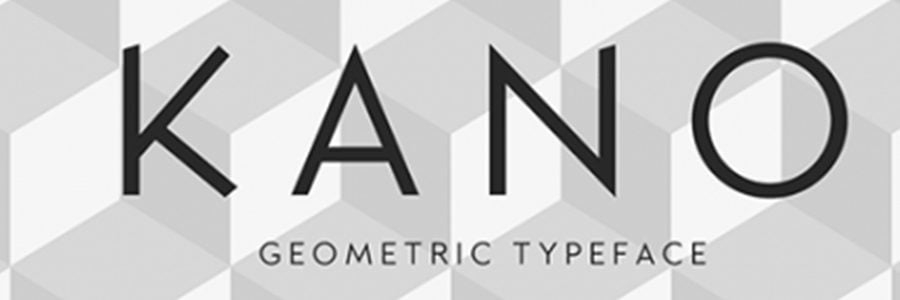
Kano : Typographie géométrique et gratuite
Kano est une typographie désignée par Frederick Lee et créée avec une structure géométrique.
Cette typographie est idéale pour la conception de logos, affiches, cartes de visite, flyers ou dépliants.